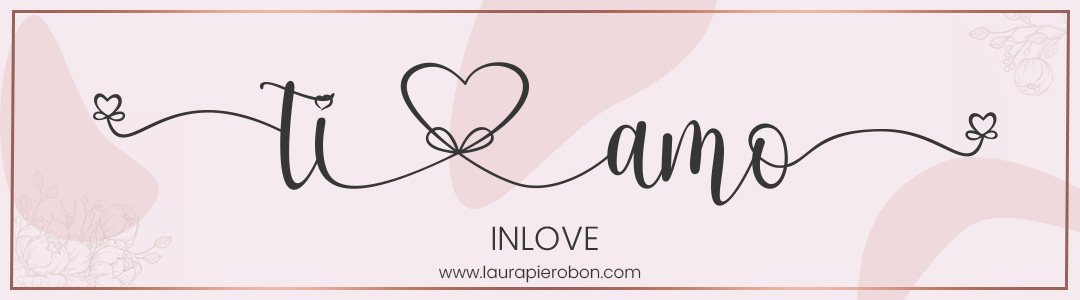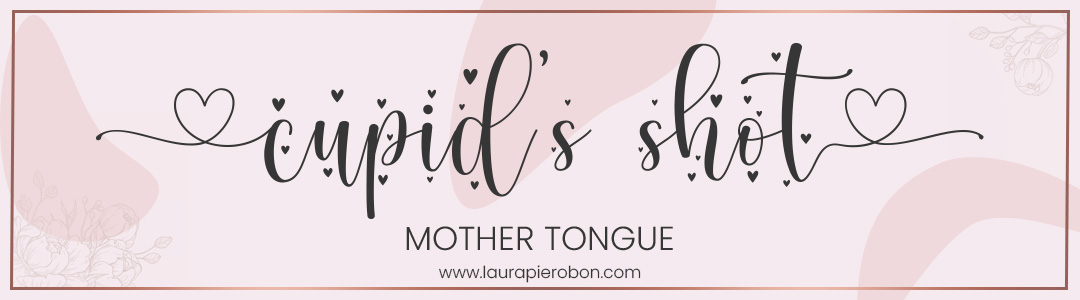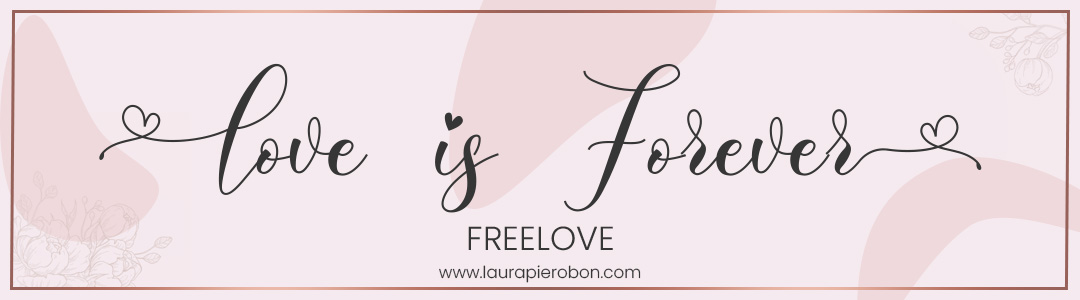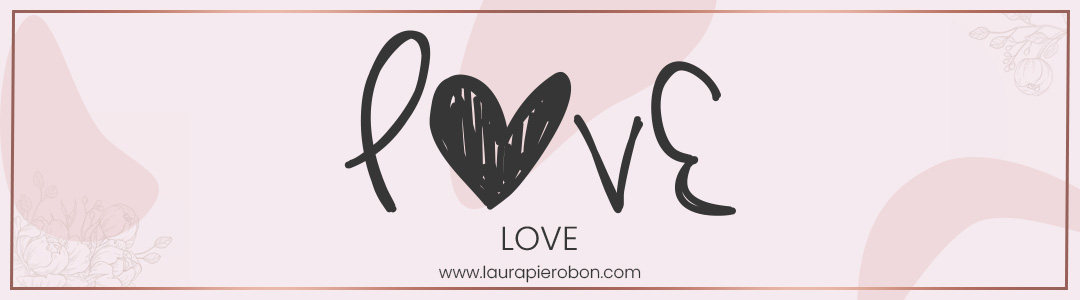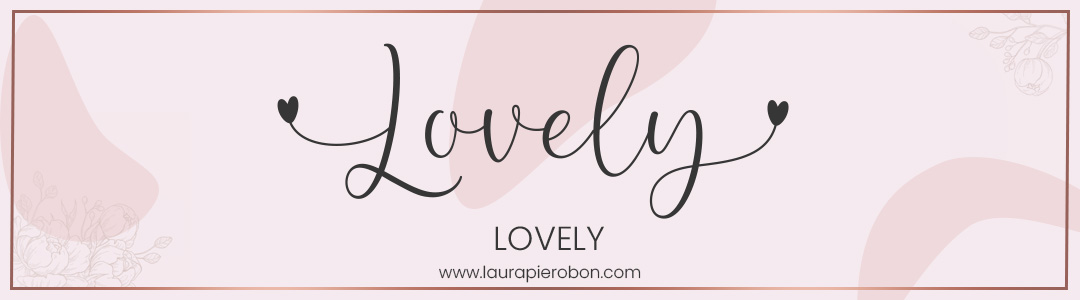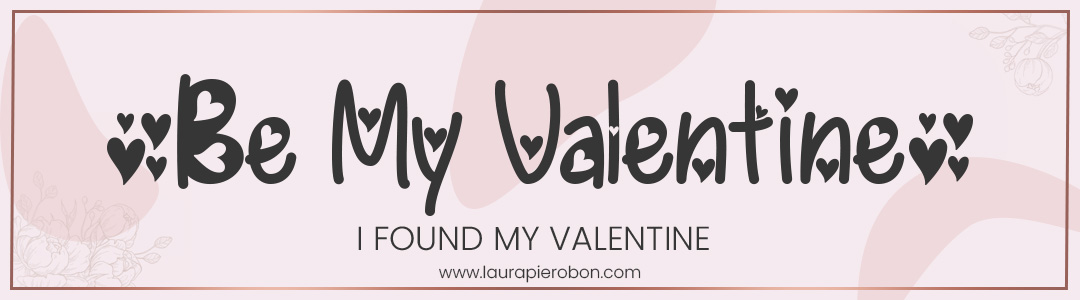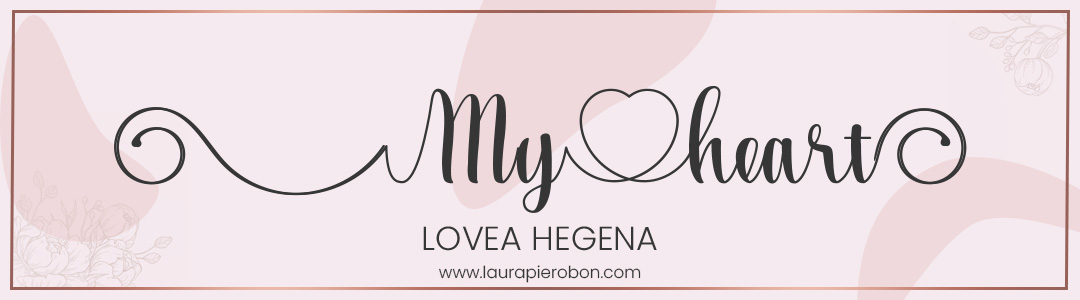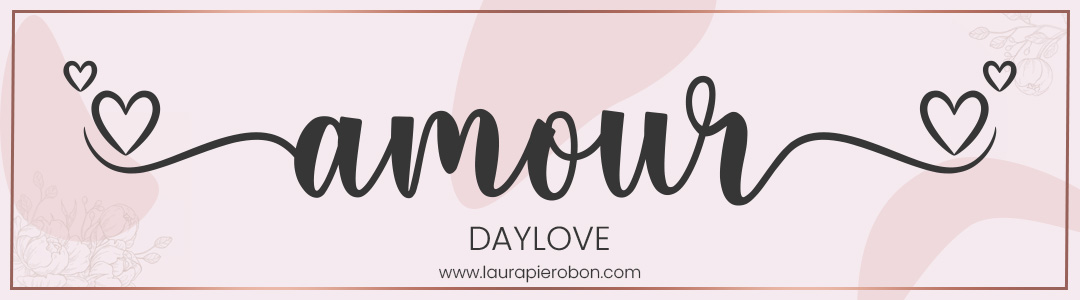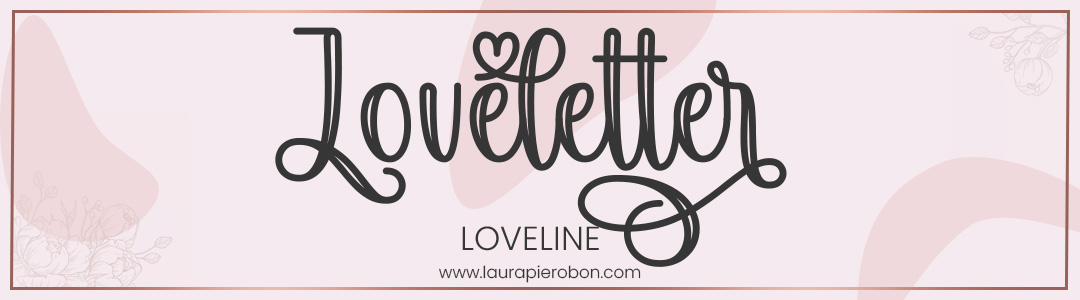
San Valentino è l’occasione perfetta per dare spazio alla creatività e all’amore ❤️.
Un biglietto speciale, una grafica personalizzata, un post per i social o persino un piccolo progetto di branding: tutto acquista più magia se accompagnato da un font che parli di romanticismo.
In questa raccolta ho selezionato per te 10 font display gratuiti da scaricare su Dafont.com: sono caratteri eleganti, decorativi e originali, perfetti per celebrare l’amore in tutte le sue sfumature.
💌 10 font romantici da scaricare subito
- Inlove – Semplice ma d’impatto, con un tratto morbido che trasmette calore e dolcezza.
Freelove – Frizzante e giovanile, ideale per biglietti spiritosi o grafiche social romantiche ma leggere.
Love – Minimal ma immediato: ogni lettera trasuda romanticismo, ottimo per loghi e titoli.
Lovely – Dolce, rotondo e pieno di charme, perfetto per progetti delicati come partecipazioni e card.
I Found My Valentine – Già dal nome parla d’amore: un font decorativo da usare in grafiche speciali e headline a tema.
Lovea Hegena – Elegante e moderno, con un tocco calligrafico che lo rende versatile e romantico.
Daylove – Luminoso e gioioso, perfetto per dare alle tue grafiche un tono fresco e positivo.
Loveline – Lineare e pulito ma con un cuore romantico, ideale per titoli e loghi dal design semplice.
Lovebeat – Energetico e creativo, un font che trasmette passione e vivacità, adatto a progetti originali.
- Mother Tongue – Raffinato e femminile, con curve delicate che lo rendono perfetto per inviti o citazioni poetiche.